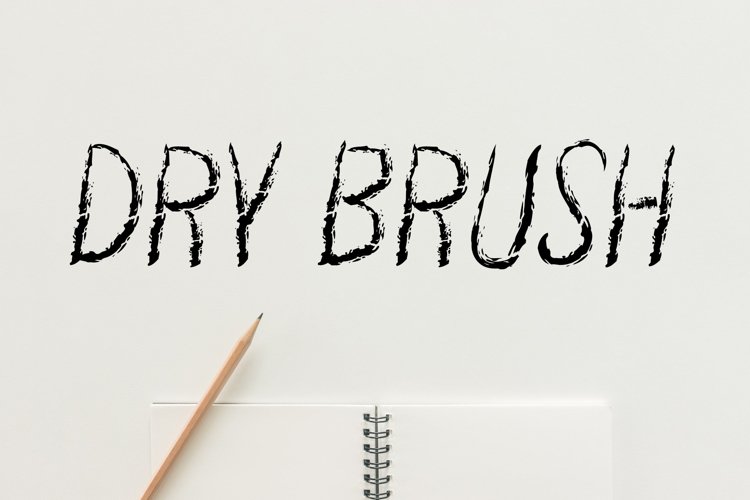
Fontbundles Dry Brush Font
[Fontbundles] Dry Brush Font
Шрифт сухой щетки для ретро стиля и ощущений.
Эскизный шрифт SVG для одежды, брендинга, приглашений, маркетинга и многого другого...